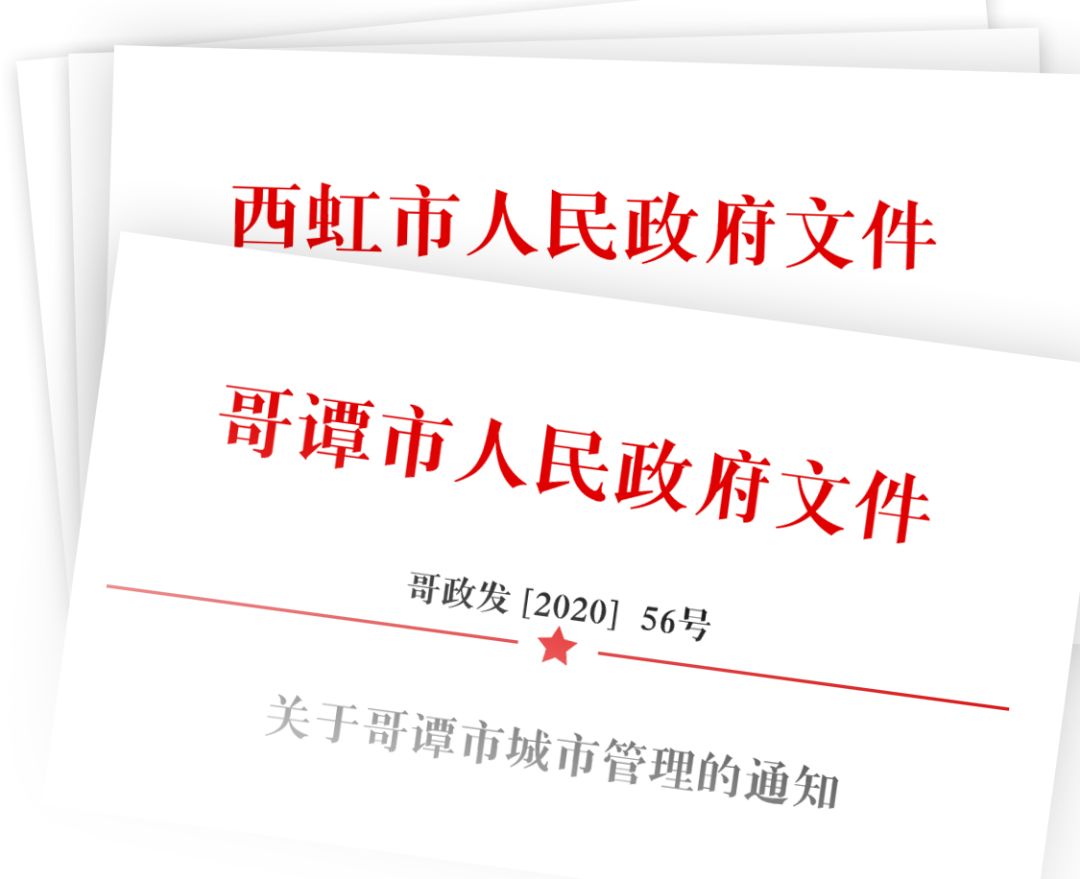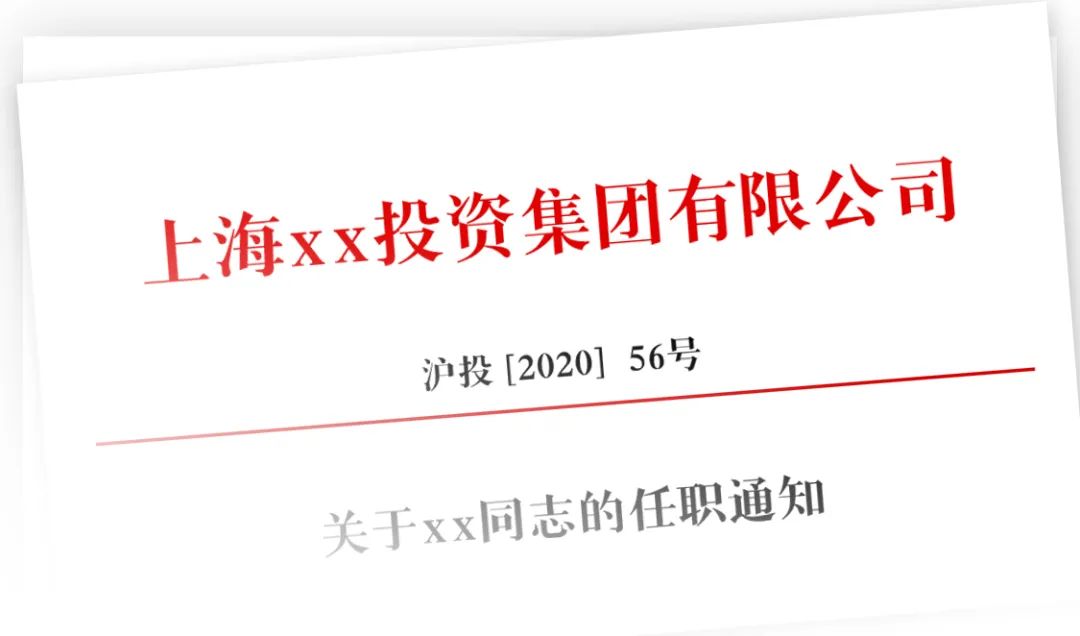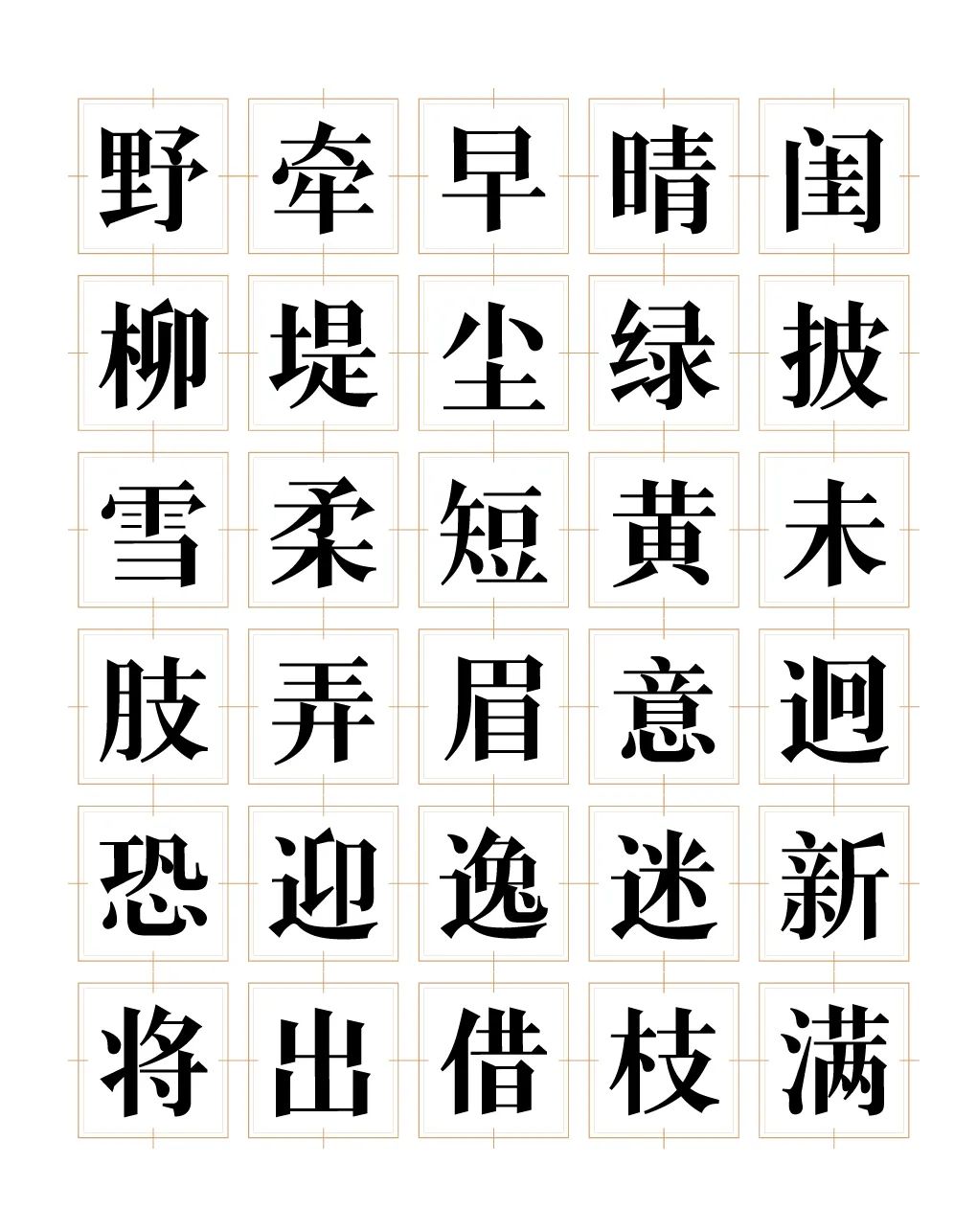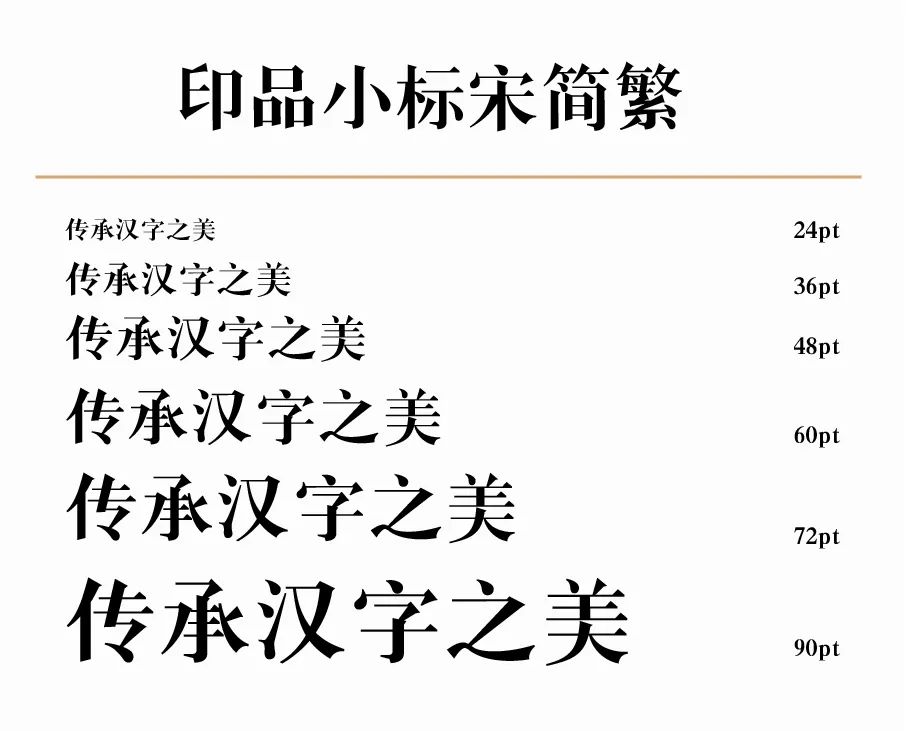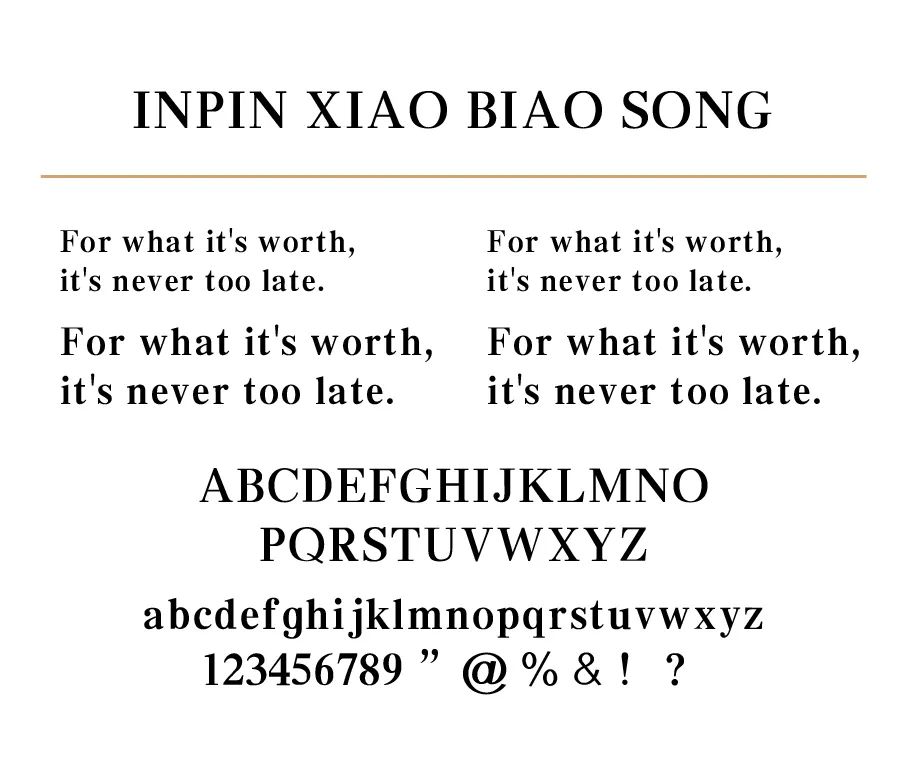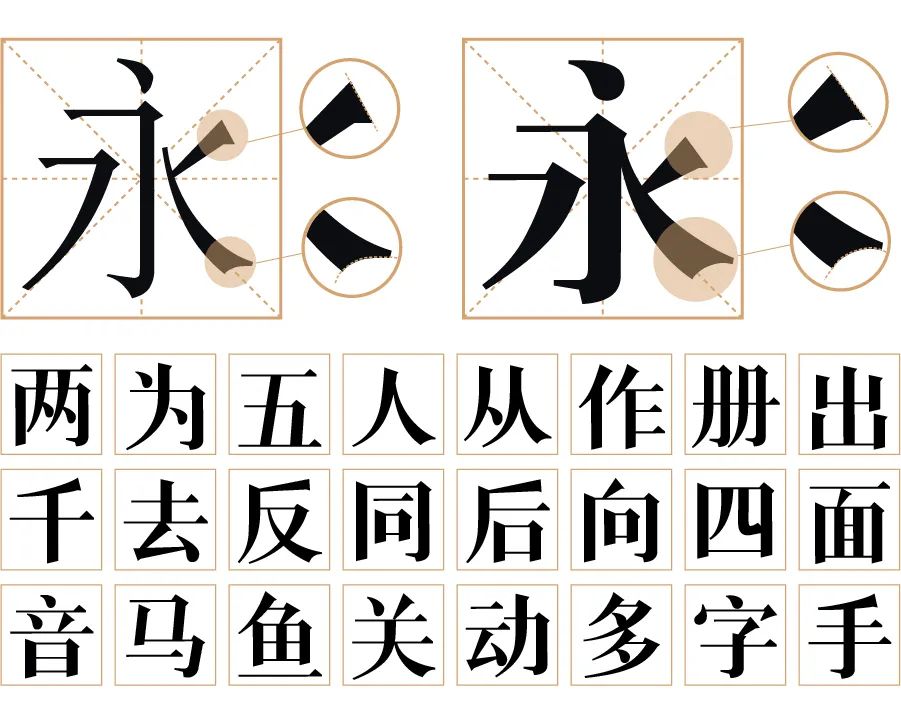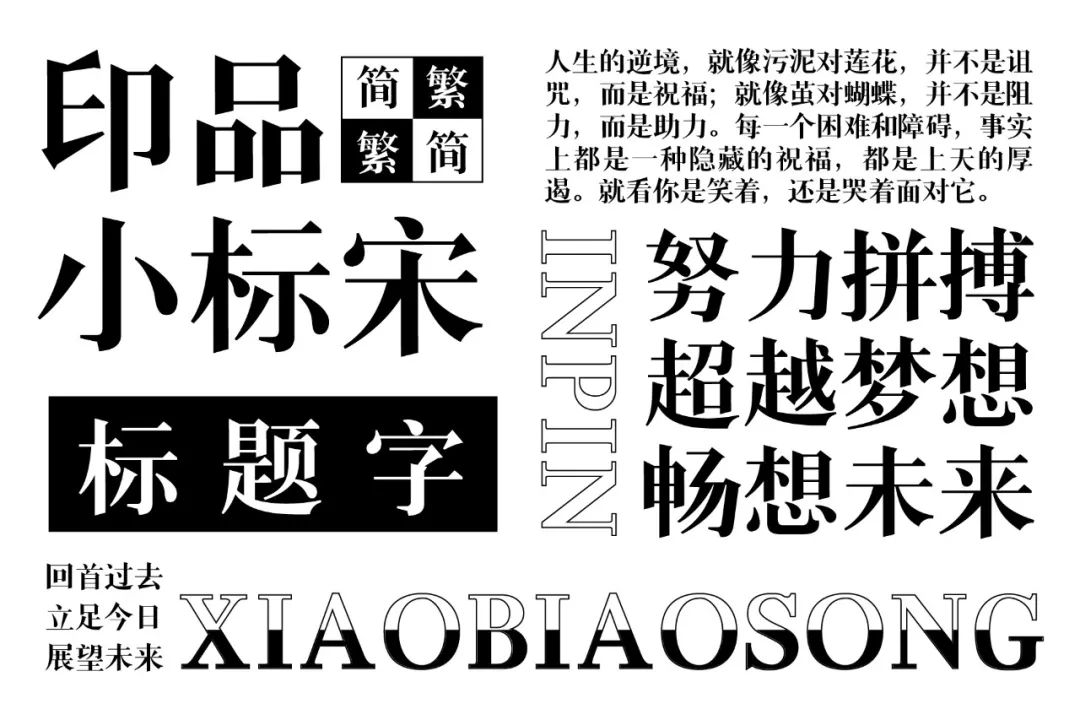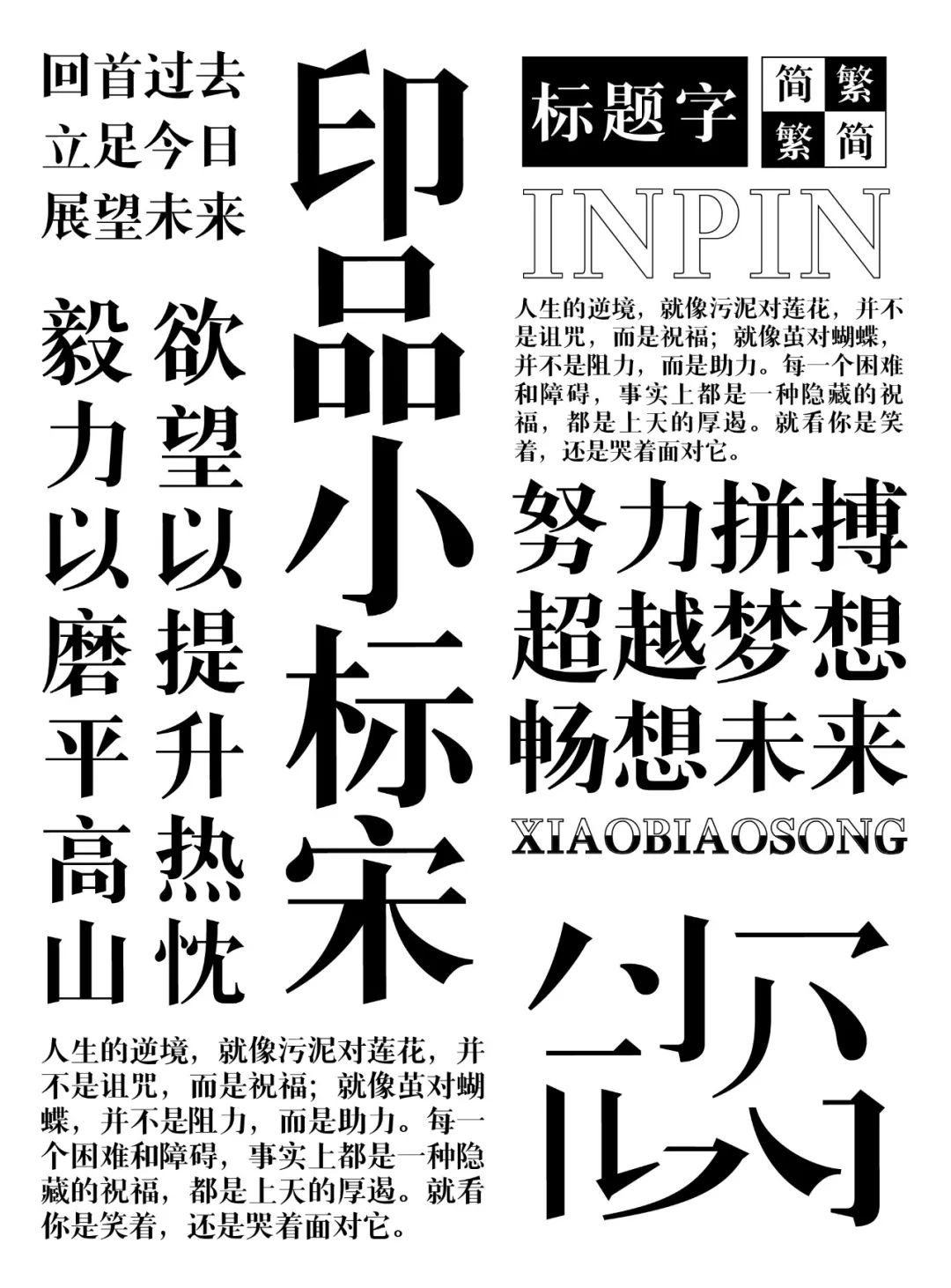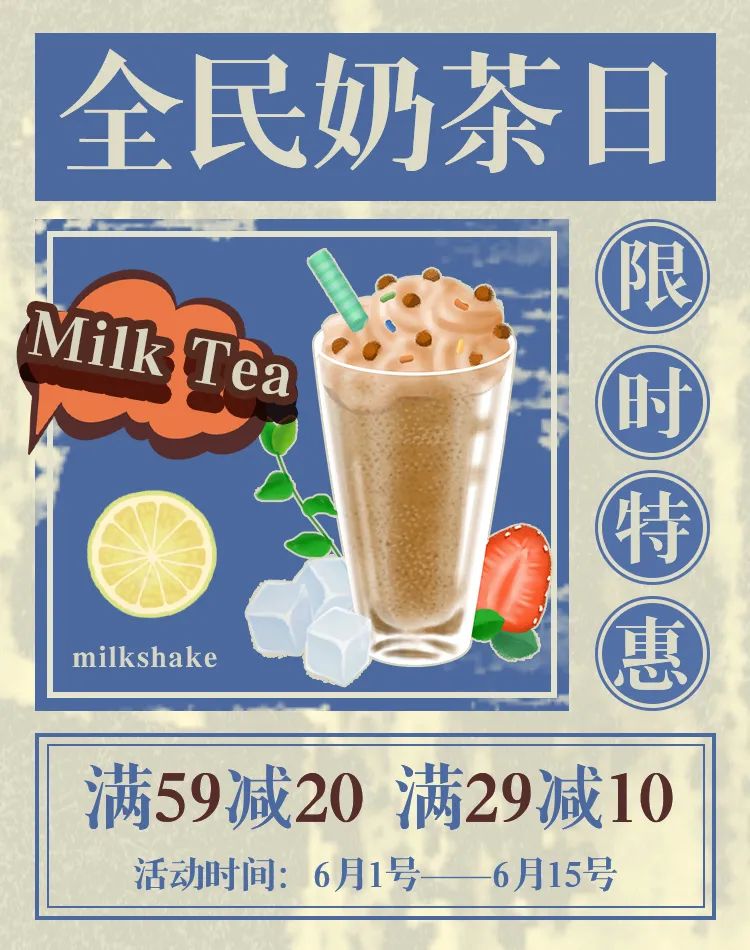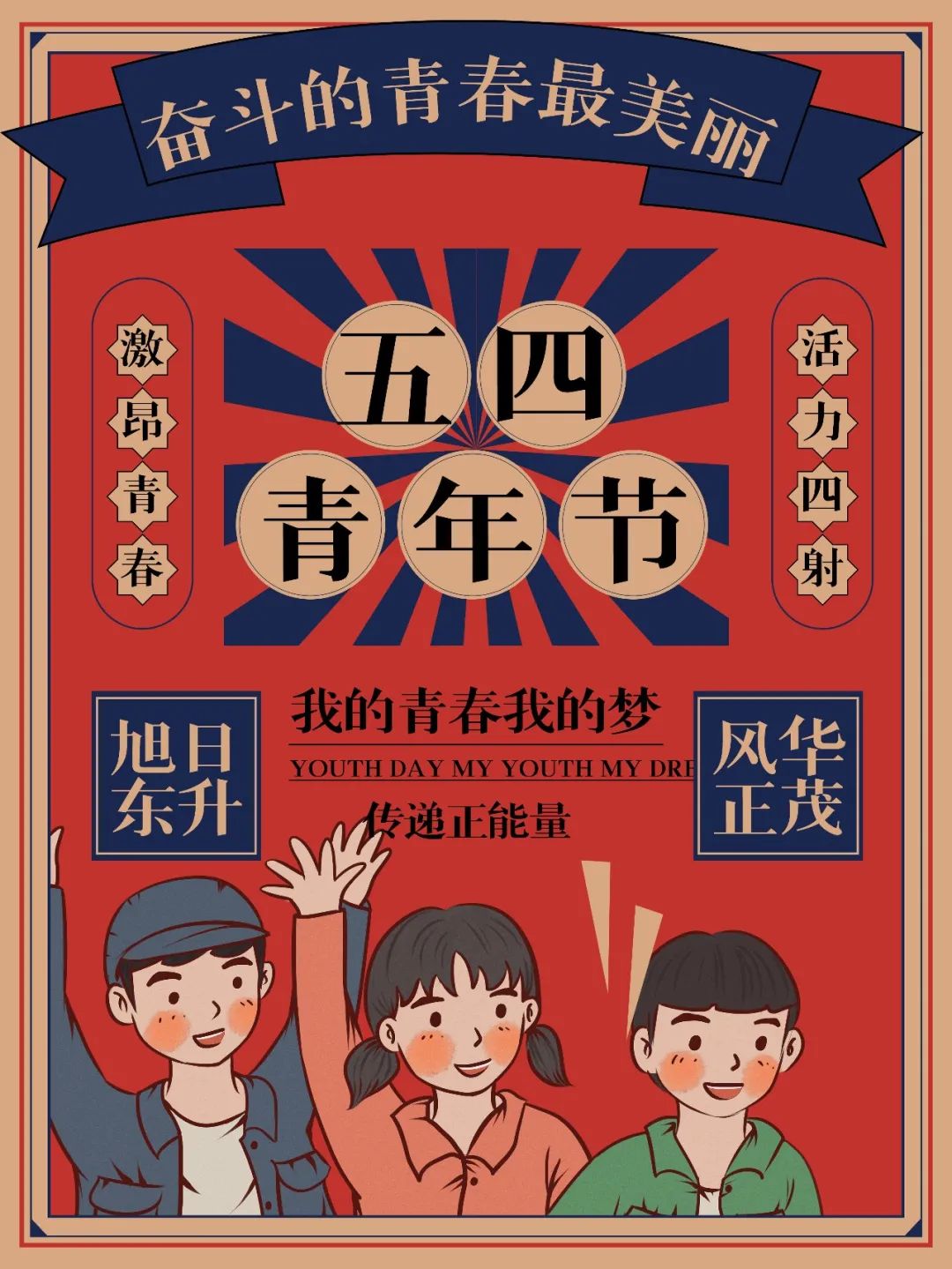
印品小标宋简繁为了满足党政机关公文用字体的高要求而专门精修的字库产品,字体美观规范、清晰易读,完全保证电子公文共享交流时统一、准确、原版的完美显示。 笔画横细竖粗,厚重而刚劲,有重力感。字形古典端庄,雍容雄秀,结构严谨而宽舒、圆满、匀称。 结构端正,显得比较硬朗,中宫比较舒展;笔画横轻竖重,横线尾呈三角状,点、撇、捺、钩等笔画有尖端,字形端正、刚劲有力。 对比普通宋体字,小标宋字体纵向的笔画非常粗重,给人以醒目之感,更有突出、强调的作用。 小标宋字体是《国家行政机关公文格式》中规定的一种标准字体,适用于政府文件中的发文机关标识、公文标题和主题词词目以及报纸、杂志、书籍、宣传册、广告、标志、包装等场景标题用字。